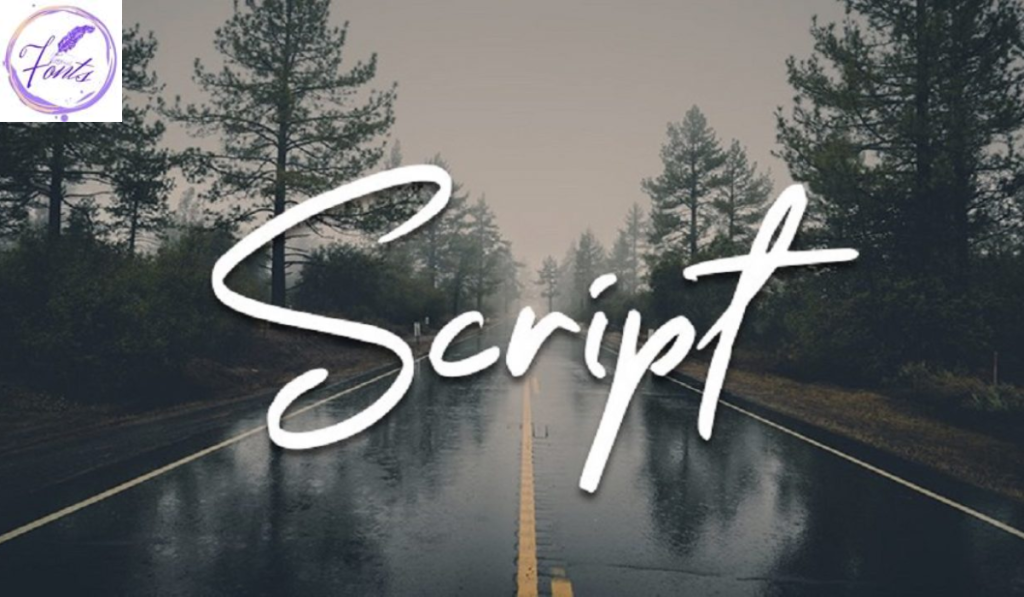
Font Script Việt hóa freestyle
Ngôn ngữ: Hỗ trợ nhiều ngôn ngữ
Phân loại: Script, viết tay, cá tính
Kiểu chữ: Không chân
Độ dày: Thin, ExtraLight, Light, Regular, Medium, SemiBold, Bold, ExtraBold, BlackĐa dạng
Font Script Việt hóa là một trong những font chữ đẹp và độc đáo nhất hiện nay. Với thiết kế mềm mại, uyển chuyển và đầy sáng tạo, font script việt hóa mang đến cho người dùng một cảm giác thư giãn và thoải mái. Dù bạn là designer chuyên nghiệp hay người dùng thông thường, font chữ này chắc chắn sẽ là lựa chọn hoàn hảo cho các dự án thiết kế của bạn. Hãy cùng khám phá những điều thú vị về font chữ script và tải về để sử dụng ngay hôm nay nhé!
Đánh giá font script việt hóa
Một trong những ưu điểm nổi bật của font script việt hóa là tính đa dạng và linh hoạt. Bạn có thể sử dụng font này cho nhiều mục đích khác nhau, từ thiết kế logo, banner cho đến các ấn phẩm quảng cáo hay thiệp cưới. Bên cạnh đó, font script việt hóa cũng rất dễ kết hợp với các phần tử thiết kế khác, giúp tạo ra những tác phẩm độc đáo và ấn tượng. Với chất lượng cao và tính năng vượt trội, freestyle script việt hóa xứng đáng là một trong những font chữ được yêu thích nhất hiện nay.